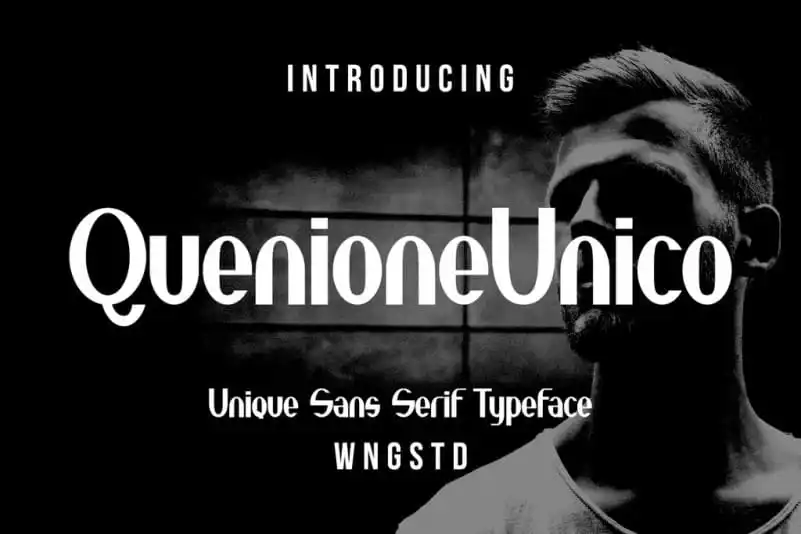
Quenione Unico Sans Serif Font – Download Grátis
A Quenione Unico Sans Serif é uma elegante tipografia sans serif com contraste forte, criada pelo designer WNGSTD no ambiente 99designs. Com seu design clássico e único, esta fonte se destaca por sua alta contraste de caracteres que a torna perfeita tanto para mídia tradicional quanto para o web. Ela é ideia ideal para os entusiastas do crochê ou gráficos profissionais. Além disso, é compatível com todas as ferramentas e pode inspirar projetos criativos como revistas inspiradoras ou a criação de identidade de marca. Sem dúvida, uma opção versátil que adiciona um toque distintivo em qualquer projeto visual.